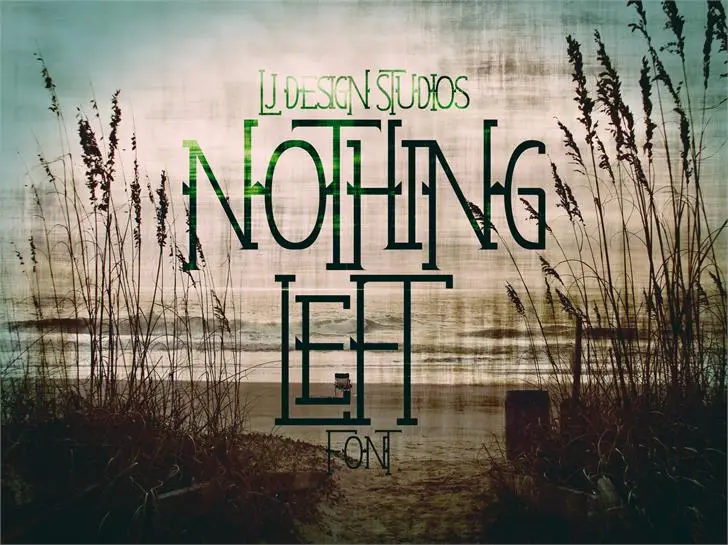
Nothing Left font – Download Grátis
A Nothing Left é uma elegante e poderosa fonte do tipo Blackletter, criada pelo designer Hamilton. Seu design robusto e arredondado traz consigo uma atmosfera sombria e sofisticada que se encaixa perfeitamente para aplicações gráficas como logotipos de marca, capas de livros de literatura gótica ou mesmo para aplicativos de segurança onde criptografia é essencial. A Nothing Left não apenas oferece uma variedade robusta e versátil de letras maiúsculas e minúsculas, números e símbolos; mas também tem a vantagem de permitir um alto grau de personalização com caracteres bloqueados que podem ser usados ou excluídos conforme necessário. Para usuários comerciais desejosos de explorar todas as potenciais aplicações do design da fonte Nothing Left, eles têm o acesso direto através deste link específico. Para mais informações, os interessados também podem entrar em contato diretamente com Hamilton por e-mail ou telefone. Ainda que a Nothing Left seja uma fonte criada para o uso comercial, ela oferece flexibilidade adicional ao permitir a exclusão de qualquer característica desejada. Esta opção permite personalização ainda maior e um ajuste perfeito às necessidades específicas do projeto em mãos.